Tháng 7 là thời điểm nhiều designer làm mới thư viện chữ để phục vụ các dự án branding, social media, bao bì, editorial và giao diện số. Bài viết này tuyển chọn 10 font Việt hóa đáng chú ý, phân tích cá tính thị giác, khả năng ứng dụng và lưu ý sử dụng để bạn chọn đúng kiểu chữ cho từng mục tiêu thiết kế.
Top 10 Font Việt Hóa Đáng Chú Ý Nhất Tháng 7 Dành Cho Designer
1. Neue Montreal Việt hóa: tối giản, hiện đại và linh hoạt cho nhận diện thương hiệu
Neue Montreal là một trong những kiểu chữ sans serif được cộng đồng thiết kế quốc tế yêu thích nhờ tinh thần hiện đại, cấu trúc gọn gàng và tính ứng dụng rất rộng. Khi được Việt hóa tốt, font này trở thành lựa chọn đáng giá cho designer cần một bộ chữ cân bằng giữa sự chuyên nghiệp, trung tính và có cá tính vừa đủ. Bộ dấu tiếng Việt nếu được xử lý đúng sẽ không phá nhịp dòng, đặc biệt quan trọng trong các dự án có nhiều tiêu đề, tagline hoặc hệ thống nội dung dài.
Điểm mạnh của Neue Montreal nằm ở tỷ lệ chữ chắc, khoảng trắng thoáng và cảm giác thị giác rất sạch. Font phù hợp với nhận diện thương hiệu công nghệ, studio sáng tạo, thời trang tối giản, sản phẩm số, portfolio cá nhân và các ấn phẩm cần tạo cảm giác cao cấp nhưng không phô trương. Designer có thể dùng font này cho logo dạng chữ, heading website, deck thuyết trình, poster triển lãm hoặc hệ thống social template.
Khi sử dụng Neue Montreal Việt hóa, nên kiểm tra kỹ các cặp dấu như ấ, ẫ, ệ, ỡ, ữ trong cỡ chữ nhỏ. Một bản Việt hóa tốt cần giữ được độ rõ của dấu mà không khiến chiều cao dòng bị đội lên quá nhiều. Với tiêu đề lớn, Neue Montreal phát huy tốt khi đi cùng bố cục nhiều khoảng trắng, ảnh có tương phản mạnh và bảng màu tiết chế như đen, trắng, xám lạnh, xanh navy hoặc be trung tính.
2. Editorial New Việt hóa: thanh lịch, thời trang và giàu chất tạp chí
Editorial New mang tinh thần serif đương đại, gợi liên tưởng đến bìa tạp chí thời trang, lookbook, profile thương hiệu cao cấp và các dự án cần vẻ sang trọng. Những đường nét mảnh, độ tương phản cao giữa nét dày và nét mỏng, cùng nhịp chữ mềm mại giúp font này tạo ấn tượng ngay ở kích thước lớn. Với phiên bản Việt hóa, yếu tố quan trọng nhất là dấu phải hài hòa với trục chữ, không quá nặng và không làm mất vẻ tinh tế vốn có.
Font này rất phù hợp cho ngành thời trang, mỹ phẩm, trang sức, khách sạn boutique, nghệ thuật, nhiếp ảnh và thiết kế bìa ấn phẩm. Designer có thể dùng Editorial New Việt hóa cho headline, tiêu đề chiến dịch, quote, tên bộ sưu tập hoặc layout editorial nhiều tính trình diễn. Tuy nhiên, đây không phải kiểu chữ lý tưởng cho đoạn văn dài ở cỡ nhỏ vì độ tương phản cao có thể làm mắt mỏi khi đọc trên màn hình.
Một cách dùng hiệu quả là kết hợp Editorial New với một sans serif trung tính như Neue Montreal, Satoshi hoặc General Sans. Serif đảm nhiệm vai trò tạo cảm xúc và điểm nhấn, trong khi sans serif xử lý phần thông tin, mô tả sản phẩm, giá, chú thích hoặc điều hướng. Sự tương phản giữa hai nhóm chữ giúp thiết kế vừa có tính biên tập, vừa đảm bảo khả năng đọc.
3. Satoshi Việt hóa: thân thiện, sắc nét và phù hợp sản phẩm số
Satoshi là lựa chọn đáng chú ý cho designer làm việc với giao diện người dùng, landing page, dashboard, app mobile và thương hiệu startup. Font có cấu trúc hình học nhẹ, nét chữ rõ ràng, cảm giác trẻ nhưng không quá nghịch. Khi Việt hóa tốt, Satoshi giữ được sự mượt mà trong các cụm chữ có dấu, đặc biệt là những từ tiếng Việt dài thường xuất hiện trong nút bấm, menu, thông báo và mô tả chức năng.
Ưu điểm lớn của Satoshi là khả năng hoạt động ổn định trong nhiều kích thước. Ở cỡ nhỏ, chữ vẫn rõ; ở cỡ lớn, font không bị nhạt nhòa. Điều này giúp designer xây dựng hệ thống typography thống nhất cho website, ứng dụng, bộ nhận diện nội bộ hoặc tài liệu thương mại. Satoshi cũng có nhiều weight, thuận tiện để tạo phân cấp nội dung mà không cần dùng quá nhiều font khác nhau.
Với các dự án công nghệ, giáo dục trực tuyến, fintech, SaaS hoặc nền tảng cộng đồng, Satoshi Việt hóa mang lại cảm giác tin cậy và dễ tiếp cận. Designer nên chú ý line-height khi dùng cho tiếng Việt, vì dấu thanh có thể cần thêm khoảng thở so với tiếng Anh. Một line-height từ 140% đến 160% thường an toàn cho đoạn văn trên website, trong khi heading có thể dùng chặt hơn để tạo độ chắc.
Những Font Việt Hóa Nổi Bật Cho Branding, Poster Và Social Media
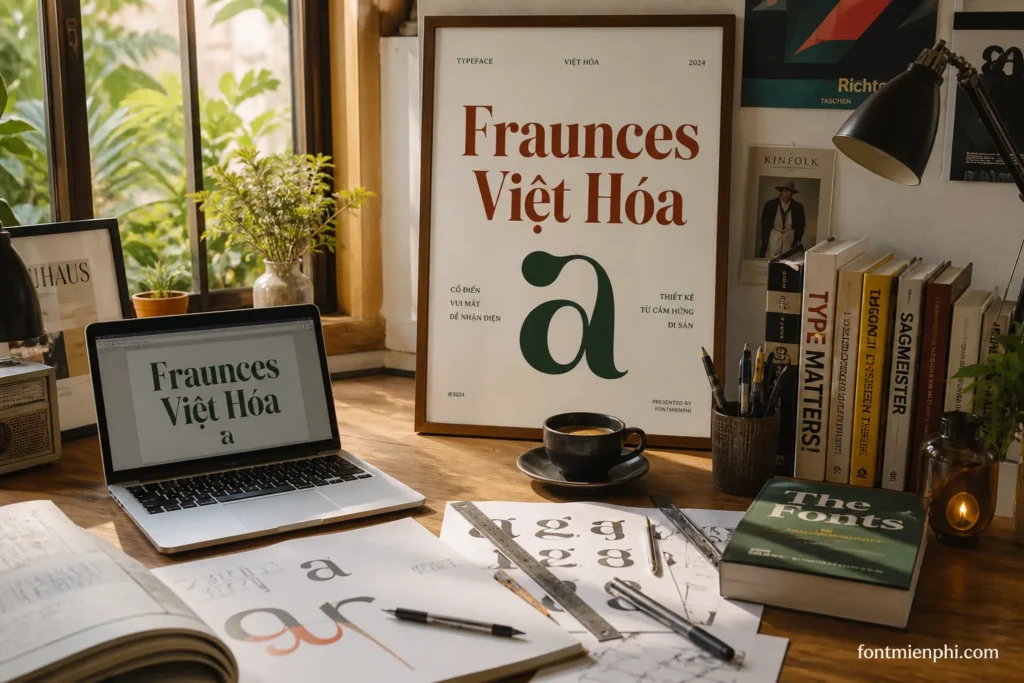
4. Fraunces Việt hóa: cổ điển, vui mắt và có độ nhận diện cao
Fraunces là một serif giàu cá tính, kết hợp cảm giác cổ điển với tinh thần vui tươi. Điểm hấp dẫn của font này là các đường cong mềm, độ tương phản linh hoạt và khả năng tạo chất thủ công mà không bị lỗi thời. Khi được Việt hóa chỉn chu, Fraunces có thể trở thành điểm nhấn mạnh trong các dự án F&B, cà phê, bánh ngọt, cửa hàng thủ công, thương hiệu lifestyle hoặc chiến dịch truyền thông cần vẻ ấm áp.
Font này đặc biệt hiệu quả trong poster, nhãn bao bì, tiêu đề menu, bao thư, sticker và bài đăng social media. So với các serif nghiêm trang, Fraunces có nhiều năng lượng hơn, tạo cảm giác gần gũi và giàu tính kể chuyện. Nếu thương hiệu muốn truyền tải sự tự nhiên, vui vẻ, hoài niệm nhẹ hoặc tinh thần boutique, đây là lựa chọn rất đáng cân nhắc.
➡️ Xem thêm: Hướng Dẫn Sử Dụng Font Trong Photoshop Chuẩn Designer 2026
Khi dùng Fraunces Việt hóa, designer nên tránh lạm dụng ở toàn bộ văn bản. Font đẹp nhất khi xuất hiện ở vị trí chính: tên sản phẩm, headline, câu slogan hoặc con số nổi bật. Phần nội dung phụ có thể dùng sans serif đơn giản để cân bằng. Bảng màu đi cùng Fraunces nên có chất liệu rõ như kem, nâu, xanh olive, đỏ gạch, vàng bơ hoặc các gam pastel có độ trầm.
5. Clash Display Việt hóa: mạnh mẽ, sắc cạnh và hợp xu hướng visual bold
Clash Display là kiểu chữ display sans serif có hình khối rõ, tỷ lệ táo bạo và cảm giác rất hợp với thiết kế đương đại. Font này thường được dùng cho poster âm nhạc, thời trang đường phố, thương hiệu sáng tạo, landing page sự kiện và các chiến dịch cần gây chú ý nhanh. Với phiên bản Việt hóa, điểm cần quan tâm là dấu phải đủ nổi nhưng không làm mất cấu trúc mạnh của chữ cái.
Clash Display không phải font dành cho mọi dự án, nhưng khi dùng đúng ngữ cảnh, nó tạo hiệu ứng thị giác rất tốt. Chữ có cá tính mạnh, phù hợp với bố cục lớn, tương phản cao, ảnh cắt phá cách, gradient đậm hoặc nền texture. Designer có thể dùng font này cho tiêu đề chính, key visual, thumbnail, cover video, poster sự kiện, bộ nhận diện tạm thời cho campaign hoặc các thiết kế có tinh thần experimental.
Điểm cần tránh là dùng Clash Display cho đoạn văn dài hoặc giao diện cần sự nghiêm túc cao. Font có độ trình diễn lớn nên nếu xuất hiện quá nhiều sẽ gây mệt mắt và làm giảm giá trị nhấn mạnh. Một công thức an toàn là dùng Clash Display cho 5% nội dung quan trọng nhất, sau đó kết hợp với một sans serif dễ đọc cho phần còn lại.
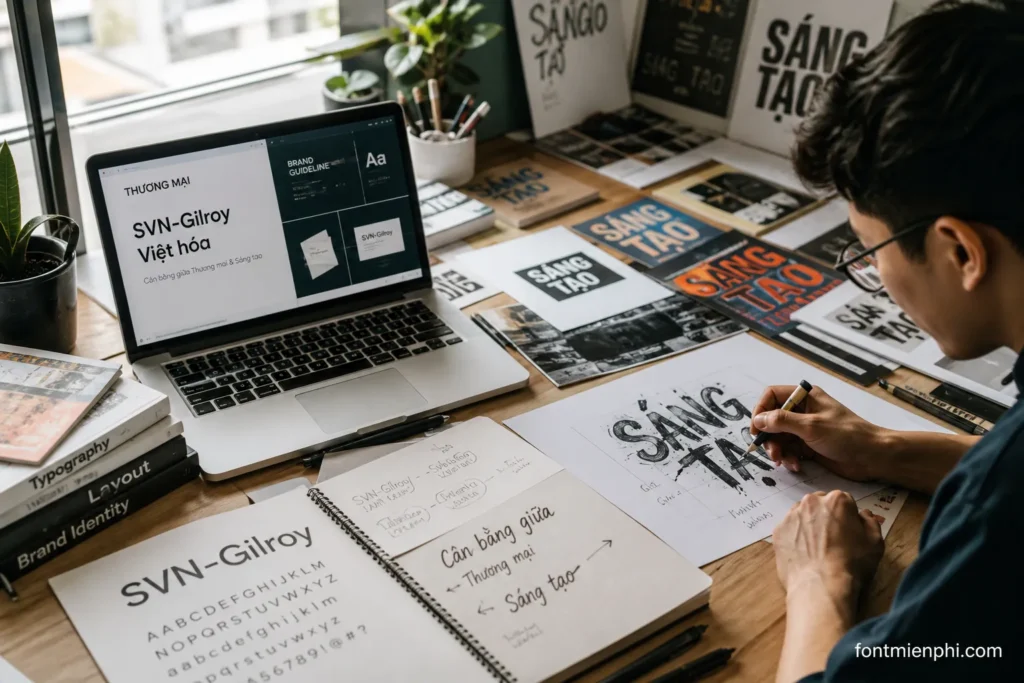
6. SVN-Gilroy Việt hóa: cân bằng giữa thương mại và sáng tạo
Gilroy là một trong những font geometric sans phổ biến trong thiết kế thương mại nhờ cảm giác sạch, hiện đại và dễ dùng. Phiên bản Việt hóa của Gilroy được nhiều designer lựa chọn cho thương hiệu bán lẻ, bất động sản, giáo dục, công nghệ, mỹ phẩm và các dự án marketing cần vẻ chuyên nghiệp. Cấu trúc chữ tròn, đều và sáng giúp font này thân thiện hơn nhiều kiểu sans serif quá lạnh hoặc quá kỹ thuật.
Trong thực tế, Gilroy Việt hóa hoạt động tốt ở cả heading lẫn body text nếu chọn weight phù hợp. Light và Regular tạo cảm giác thanh thoát; Medium và Semibold phù hợp cho nhấn mạnh; Bold và ExtraBold có thể dùng cho banner, tiêu đề sale hoặc key message. Đây là một lợi thế lớn khi designer cần xây dựng hệ thống nhận diện nhanh, đồng bộ và dễ bàn giao cho đội marketing.
Để tránh cảm giác quá phổ biến, designer nên tạo khác biệt bằng cách xử lý bố cục, khoảng cách chữ, màu sắc và hình ảnh đi kèm. Gilroy đẹp khi được dùng trong layout có grid rõ ràng, icon đồng bộ và khoảng trắng hợp lý. Nếu làm branding, có thể tùy biến nhẹ một vài ký tự trong logotype thay vì dùng nguyên bản để tăng tính riêng biệt.
Font Việt Hóa Cho Nội Dung Dài, Giao Diện Và Ấn Phẩm Chuyên Nghiệp
7. Be Vietnam Pro: tối ưu tiếng Việt, dễ đọc và đáng tin cậy
Be Vietnam Pro là font được thiết kế với sự quan tâm rõ ràng đến tiếng Việt, vì vậy đây là lựa chọn rất an toàn cho các dự án cần khả năng đọc cao. Font có bộ dấu ổn định, hình dáng chữ cân bằng và phù hợp với nhiều môi trường hiển thị. Với designer thường làm website, app, báo cáo, tài liệu thương hiệu hoặc nội dung giáo dục, Be Vietnam Pro là một công cụ thực dụng và đáng tin cậy.
Điểm mạnh của Be Vietnam Pro không nằm ở sự phô diễn mà nằm ở tính bền vững. Khi một dự án có nhiều trang, nhiều cấp thông tin và nhiều người cùng sử dụng, font cần ít lỗi, dễ đọc, dễ triển khai và không gây tranh cãi. Be Vietnam Pro đáp ứng tốt các yêu cầu này, đặc biệt trong giao diện tiếng Việt có nhiều câu dài và nhiều dấu thanh.
Designer có thể dùng Be Vietnam Pro cho body text, caption, form, bảng dữ liệu, tài liệu nội bộ, hồ sơ năng lực hoặc landing page. Nếu muốn tạo điểm nhấn, hãy kết hợp nó với một display font giàu cá tính cho heading. Cách phối này giúp tổng thể vừa có tính nhận diện, vừa đảm bảo trải nghiệm đọc ổn định ở phần nội dung chính.
8. IBM Plex Sans Việt hóa: nghiêm túc, kỹ thuật và phù hợp hệ thống lớn
IBM Plex Sans là một font sans serif có tinh thần công nghệ, rõ ràng và chuyên nghiệp. Font được đánh giá cao nhờ tính hệ thống, nhiều weight, nhiều kiểu chữ và khả năng dùng trong các sản phẩm có cấu trúc thông tin phức tạp. Với bản Việt hóa tốt, IBM Plex Sans đặc biệt phù hợp cho dashboard, tài liệu kỹ thuật, sản phẩm B2B, ngân hàng số, bảo hiểm, y tế, giáo dục và các nền tảng dữ liệu.
So với các font geometric mềm mại, IBM Plex Sans có cảm giác lý trí và trưởng thành hơn. Nó không cố tạo sự thời thượng mà tập trung vào khả năng truyền đạt. Đây là ưu điểm lớn trong những dự án mà độ tin cậy quan trọng hơn hiệu ứng thị giác. Khi dùng cho tiếng Việt, font giữ nhịp đọc tốt nếu khoảng cách dòng và độ tương phản màu được thiết lập hợp lý.
IBM Plex Sans Việt hóa có thể đi cùng IBM Plex Serif hoặc IBM Plex Mono để tạo một hệ typography đa dạng nhưng thống nhất. Sans dùng cho giao diện và nội dung chính, Serif dùng cho ấn phẩm trang trọng, Mono dùng cho mã, dữ liệu hoặc nhãn kỹ thuật. Sự đồng bộ này rất hữu ích khi xây dựng design system cho tổ chức lớn.
9. Lora Việt hóa: mềm mại, dễ đọc và phù hợp kể chuyện thương hiệu
Lora là một serif có độ đọc tốt, mang cảm giác văn chương nhẹ và giàu tính nhân văn. Khác với các display serif quá mảnh, Lora đủ chắc để dùng cho đoạn văn dài, đặc biệt trong blog, bài PR, website thương hiệu, ấn phẩm du lịch, giáo dục, chăm sóc sức khỏe hoặc các dự án cần giọng điệu ấm áp. Phiên bản Việt hóa tốt giúp dấu tiếng Việt hòa vào dòng chữ tự nhiên, không gây cảm giác bị gắn thêm.
Font này phù hợp với những thương hiệu muốn nói chuyện bằng cảm xúc, câu chuyện và sự tin cậy. Khi dùng Lora cho body text, người đọc có cảm giác chậm lại và tập trung hơn so với nhiều sans serif hiện đại. Điều này rất hữu ích cho nội dung editorial, bài giới thiệu nhà sáng lập, câu chuyện sản phẩm, hồ sơ nghệ nhân hoặc landing page có phần storytelling dài.
Lora Việt hóa cũng hoạt động tốt khi kết hợp với sans serif tối giản cho menu, nút bấm và chú thích. Designer nên chọn cỡ chữ đủ lớn, line-height thoáng và độ tương phản màu vừa phải để tạo trải nghiệm đọc dễ chịu. Trên nền giấy hoặc nền màu kem, Lora cho cảm giác gần gũi và có chiều sâu hơn so với nền trắng thuần.
Cách Chọn Font Việt Hóa Đúng Cho Dự Án Thiết Kế Tháng 7
10. Việt hóa không chỉ là thêm dấu, mà là tối ưu trải nghiệm đọc
Một font Việt hóa đáng dùng không chỉ cần hiển thị đủ ký tự tiếng Việt. Điều quan trọng hơn là dấu phải đúng vị trí, tỷ lệ dấu hài hòa, khoảng cách chữ ổn định và không làm vỡ nhịp thị giác của font gốc. Nhiều bản Việt hóa kém có thể trông ổn ở một vài chữ đơn lẻ nhưng gặp vấn đề khi đặt trong câu dài, tiêu đề nhiều dấu hoặc bố cục nhỏ trên mobile.
Khi đánh giá một font Việt hóa, designer nên thử bằng văn bản thật thay vì chỉ nhìn specimen đẹp. Hãy kiểm tra các cụm từ có nhiều dấu như “tối ưu trải nghiệm”, “định vị thương hiệu”, “sản phẩm sáng tạo”, “cộng đồng thiết kế”, “khả năng chuyển đổi” hoặc “nghiên cứu người dùng”. Những cụm này giúp phát hiện nhanh lỗi va chạm dấu, lệch dấu, khoảng cách không đều và độ cao dòng bất hợp lý.
Designer cũng cần chú ý giấy phép sử dụng. Một font đẹp nhưng không rõ license có thể tạo rủi ro cho dự án thương mại. Trước khi dùng cho logo, bao bì, website, app hoặc chiến dịch quảng cáo, nên kiểm tra quyền sử dụng cá nhân, thương mại, nhúng webfont, chỉnh sửa file font và phân phối lại trong bộ nhận diện. Đây là bước thường bị bỏ qua nhưng rất quan trọng với các dự án chuyên nghiệp.
Tiêu chí chọn font theo mục tiêu thiết kế
Không có font nào tốt nhất cho mọi hoàn cảnh. Một font phù hợp phải trả lời đúng mục tiêu truyền thông, tính cách thương hiệu, môi trường hiển thị và hành vi đọc của người dùng. Với branding cao cấp, serif như Editorial New hoặc Lora có thể tạo cảm xúc tốt. Với sản phẩm số, Satoshi, Be Vietnam Pro hoặc IBM Plex Sans giúp thông tin rõ ràng hơn. Với poster và social media, Clash Display hoặc Fraunces tạo lực hút thị giác mạnh hơn.
Nếu dự án cần sự bền vững dài hạn, hãy ưu tiên font có nhiều weight, hỗ trợ tiếng Việt ổn định, khả năng đọc tốt và giấy phép rõ ràng. Nếu dự án là campaign ngắn hạn, designer có thể chọn font giàu cá tính hơn để tăng mức độ ghi nhớ. Tuy nhiên, ngay cả với campaign, khả năng đọc vẫn không nên bị hy sinh, nhất là khi nội dung xuất hiện trên màn hình nhỏ hoặc chạy quảng cáo với thời gian nhìn rất ngắn.
Một quy trình chọn font hiệu quả có thể bắt đầu từ ba câu hỏi: thương hiệu muốn được cảm nhận như thế nào, người xem sẽ đọc nội dung ở đâu, và font có hoạt động tốt với tiếng Việt thật hay không. Sau đó, designer nên dựng nhanh một vài layout mẫu gồm headline, subheading, body text, nút bấm và caption. So sánh font trong ngữ cảnh thực tế luôn chính xác hơn việc chọn chữ chỉ dựa trên cảm hứng ban đầu.
Gợi ý phối font để thiết kế vừa đẹp vừa dễ đọc
Phối font tốt là tạo sự tương phản có kiểm soát. Một serif thanh lịch có thể đi cùng sans serif trung tính; một display font mạnh nên đi cùng body font đơn giản; một font kỹ thuật có thể được làm mềm bằng màu sắc, ảnh và khoảng trắng. Điều cần tránh là chọn hai font có cá tính quá giống nhau nhưng tỷ lệ khác nhau, vì chúng dễ tạo cảm giác lệch nhịp mà không mang lại lợi ích rõ ràng.
Với danh sách font tháng 7 này, một số hướng phối đáng thử gồm Editorial New với Neue Montreal cho thương hiệu thời trang, Fraunces với Be Vietnam Pro cho F&B, Clash Display với Satoshi cho poster công nghệ sáng tạo, Lora với IBM Plex Sans cho nội dung chuyên sâu, hoặc Gilroy với một serif mềm để cân bằng giữa thương mại và cảm xúc. Mỗi cặp font nên được kiểm tra ở cả desktop và mobile trước khi đưa vào sản xuất.
Trong thiết kế tiếng Việt, line-height thường quan trọng hơn nhiều người nghĩ. Dấu thanh làm phần trên của chữ cần thêm không gian, nhất là ở đoạn văn dài. Nếu dòng quá chặt, văn bản trở nên bí và thiếu chuyên nghiệp. Nếu dòng quá rộng, nhịp đọc bị đứt. Với body text, khoảng 1.45 đến 1.65 thường dễ đọc; với tiêu đề lớn, có thể giảm xuống tùy font và bố cục.
Lưu ý kỹ thuật khi dùng font Việt hóa trên website và sản phẩm số
Khi triển khai font Việt hóa trên website, designer và developer cần quan tâm đến dung lượng file, định dạng, font-display và fallback. Webfont quá nặng có thể làm chậm tốc độ tải trang, ảnh hưởng đến trải nghiệm người dùng và SEO. Định dạng WOFF2 thường là lựa chọn tối ưu cho web hiện đại. Nếu cần nhiều weight, chỉ nên tải những weight thật sự sử dụng thay vì nhúng toàn bộ family.
Fallback font cũng cần được thiết lập hợp lý để tránh layout bị nhảy mạnh trong lúc font chính chưa tải xong. Với tiếng Việt, fallback phải hỗ trợ dấu đầy đủ. Ngoài ra, cần kiểm tra rendering trên Windows, macOS, iOS và Android vì cùng một font có thể hiển thị hơi khác nhau giữa các hệ điều hành. Những khác biệt nhỏ ở dấu, độ đậm và độ mịn có thể ảnh hưởng đến giao diện nếu thiết kế quá sát.
Đối với sản phẩm số có nhiều dữ liệu, bảng biểu hoặc text động, nên thử font trong các trạng thái thực tế như lỗi form, thông báo dài, tên người dùng, số tiền, ngày tháng, nhãn menu và nội dung bị rút gọn. Một font đẹp trong landing page chưa chắc đã tốt trong dashboard. Ngược lại, một font có vẻ bình thường trong poster lại có thể là lựa chọn xuất sắc cho hệ thống giao diện lớn.
Xu hướng typography Việt hóa đáng chú ý trong tháng 7
Tháng 7 ghi nhận xu hướng designer Việt ưu tiên các font vừa có cá tính vừa có tính triển khai cao. Thay vì chỉ săn font lạ cho một poster đơn lẻ, nhiều người quan tâm hơn đến bộ chữ có đủ weight, hỗ trợ tiếng Việt ổn định và dùng được trên nhiều kênh. Điều này phản ánh nhu cầu thiết kế ngày càng thực tế: một font không chỉ đẹp trong moodboard mà còn phải sống tốt trong website, social media, bao bì, tài liệu bán hàng và video.
Nhóm sans serif hiện đại như Satoshi, Neue Montreal, Gilroy và Be Vietnam Pro tiếp tục được ưa chuộng vì phù hợp với nhịp làm việc nhanh của designer. Chúng dễ kết hợp, dễ mở rộng hệ thống và ít gây rủi ro khi bàn giao. Song song đó, các serif giàu cá tính như Editorial New, Fraunces và Lora được dùng nhiều hơn để tạo điểm nhấn cảm xúc, đặc biệt trong các dự án lifestyle, beauty, hospitality và nội dung thương hiệu.
Một xu hướng khác là sử dụng font display có kiểm soát. Designer không còn đặt chữ lớn chỉ để gây sốc thị giác, mà bắt đầu quan tâm nhiều hơn đến ngữ cảnh, phân cấp và khả năng đọc. Những font như Clash Display trở nên hiệu quả khi được dùng đúng liều lượng, đặt trong hệ thống layout có chủ ý và đi cùng phần chữ phụ thật rõ ràng.
Với các dự án ra mắt trong tháng 7, lựa chọn font Việt hóa nên bắt đầu từ bản sắc thương hiệu và môi trường sử dụng chính. Nếu trọng tâm là website hoặc app, hãy ưu tiên khả năng đọc, tốc độ tải và tính nhất quán. Nếu trọng tâm là chiến dịch hình ảnh, hãy chọn font có dấu ấn mạnh nhưng vẫn kiểm tra kỹ tiếng Việt ở nhiều kích thước. Nếu trọng tâm là nhận diện dài hạn, hãy đầu tư vào một hệ chữ đủ linh hoạt để phát triển cùng thương hiệu qua nhiều mùa thiết kế.